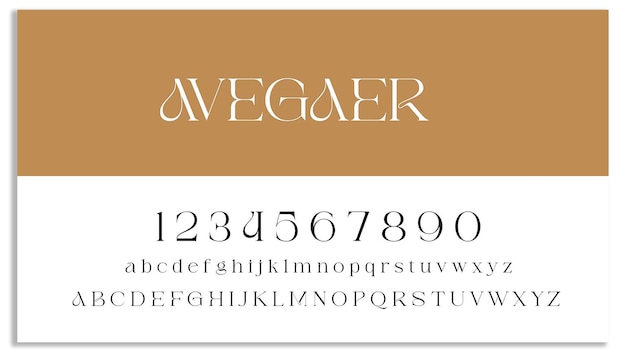
Типография роскошные классические декоративные свадебные винтажные ретро концептуальные буквы шрифт и номер Элегантные буквы алфавита шрифты с засечками векторная иллюстрация